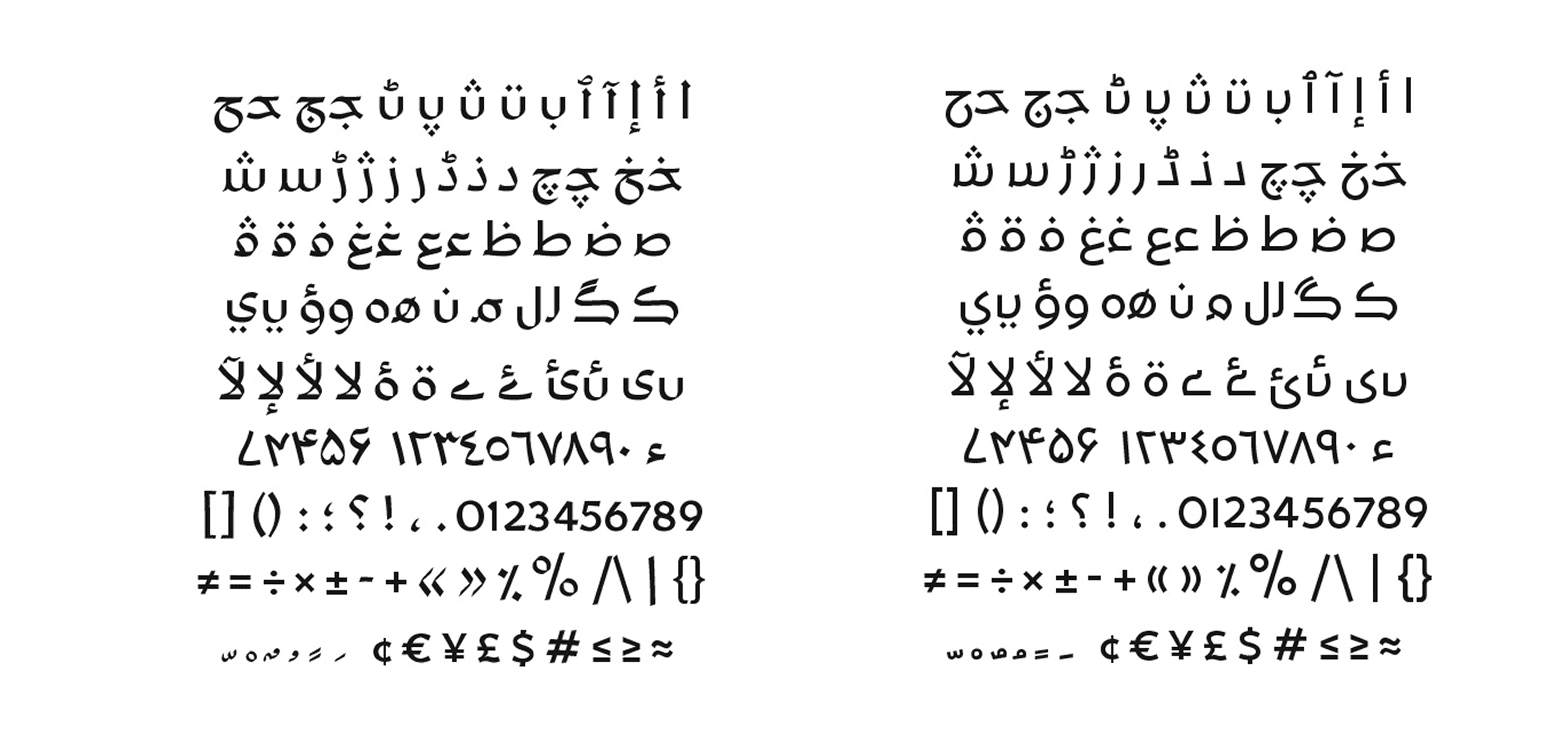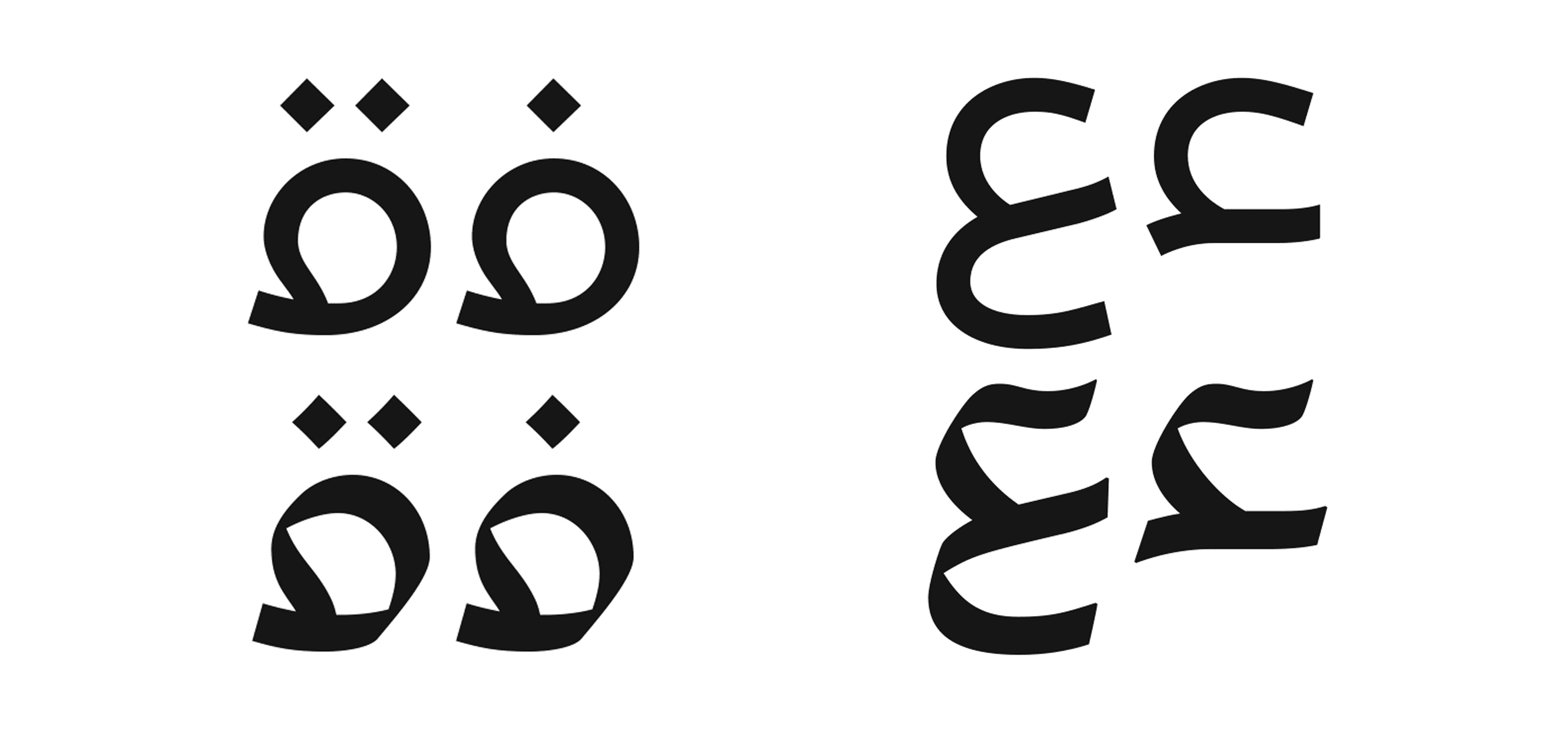
يمثل خط 29LT UA Neo تطورًا في تصميم الحروف العربية الحديثة، حيث يجمع بين البنية التقليدية والخطوط الجريئة المعاصرة. يتميز بتناسق بصري واضح يعزز من سهولة القراءة، مع تنوع كبير في الأوزان يجعله مناسبًا لمختلف الاستخدامات، من النصوص الطويلة إلى العناوين البارزة.
يُعد مثاليًا للنشر، التصميم التحريري، العلامات التجارية، والمشاريع التي تتطلب حضورًا طباعيًا متوازنًا يجمع بين الأناقة والدقة. يدعم عدة لغات ويأتي بمواصفات فنية قوية تناسب الاستخدام المهني عالي المستوى.
يمثل خط 29LT UA Neo تطورًا في تصميم الحروف العربية الحديثة، حيث يجمع بين البنية التقليدية والخطوط الجريئة المعاصرة. يتميز بتناسق بصري واضح يعزز من سهولة القراءة، مع تنوع كبير في الأوزان يجعله مناسبًا لمختلف الاستخدامات، من النصوص الطويلة إلى العناوين البارزة.
يُعد مثاليًا للنشر، التصميم التحريري، العلامات التجارية، والمشاريع التي تتطلب حضورًا طباعيًا متوازنًا يجمع بين الأناقة والدقة. يدعم عدة لغات ويأتي بمواصفات فنية قوية تناسب الاستخدام المهني عالي المستوى.
يمثل خط 29LT UA Neo تطورًا في تصميم الحروف العربية الحديثة، حيث يجمع بين البنية التقليدية والخطوط الجريئة المعاصرة. يتميز بتناسق بصري واضح يعزز من سهولة القراءة، مع تنوع كبير في الأوزان يجعله مناسبًا لمختلف الاستخدامات، من النصوص الطويلة إلى العناوين البارزة.
يُعد مثاليًا للنشر، التصميم التحريري، العلامات التجارية، والمشاريع التي تتطلب حضورًا طباعيًا متوازنًا يجمع بين الأناقة والدقة. يدعم عدة لغات ويأتي بمواصفات فنية قوية تناسب الاستخدام المهني عالي المستوى.